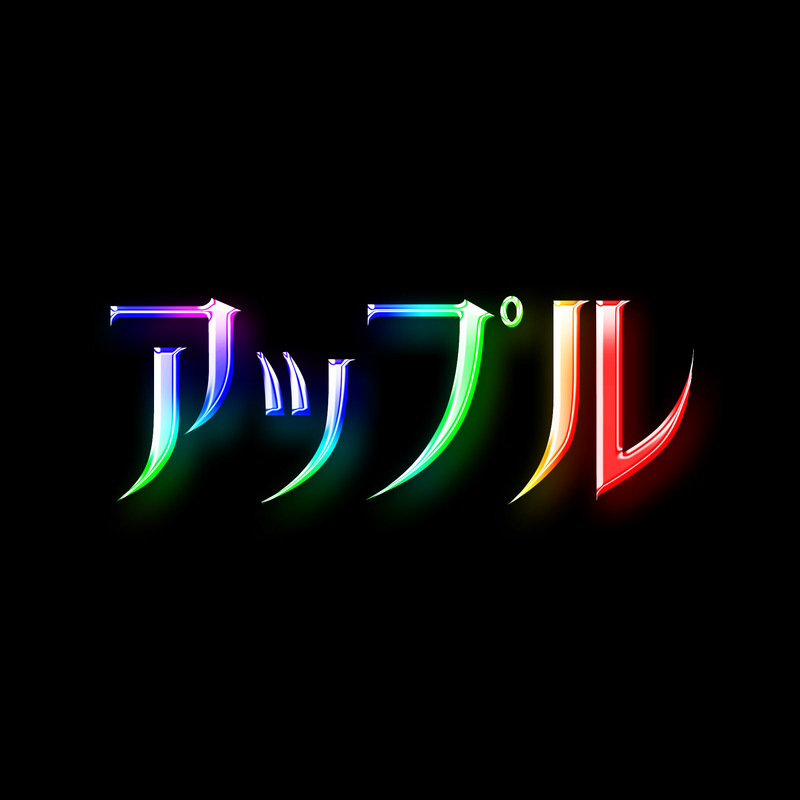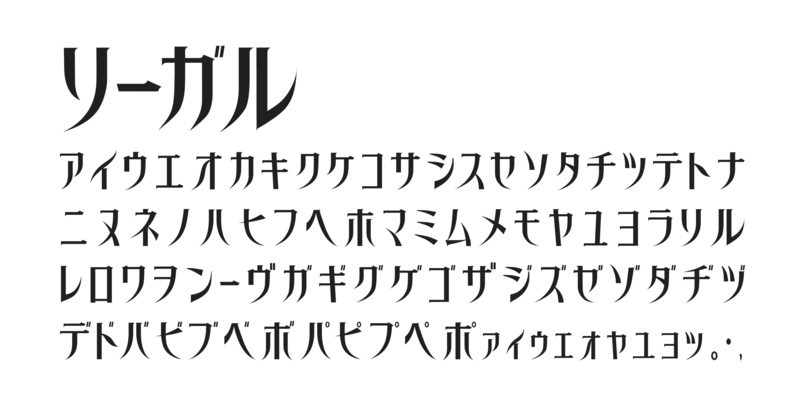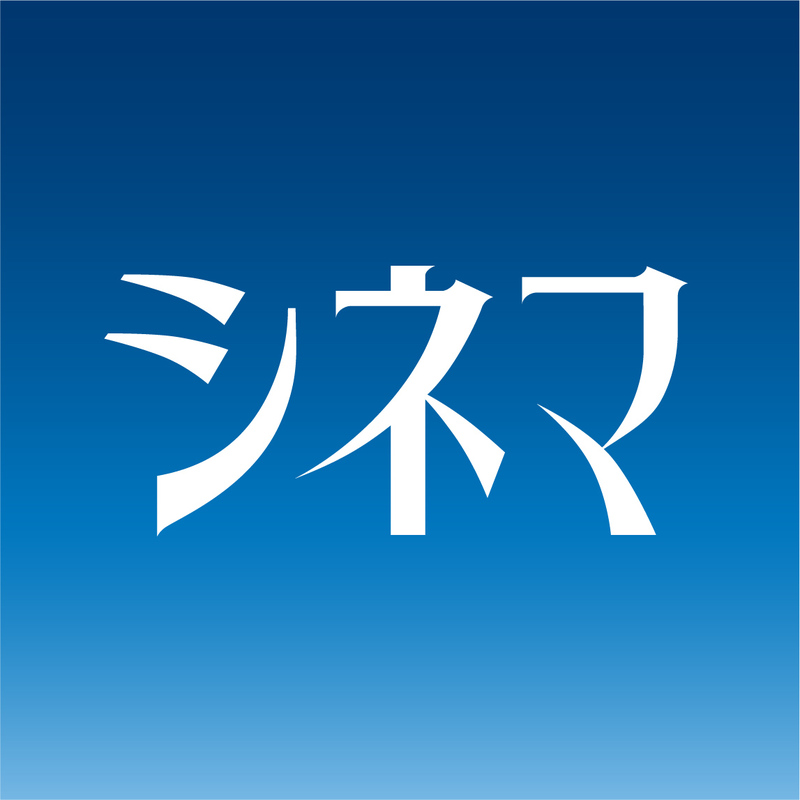
リーガル・フォント|Chiba Design|和文・欧文・デザイン書体のダウンロード販売|フォントファクトリー
商用利用可能なオリジナルフォントです。Open Type・ 2バイト・カタカナのみ。アウトライン化可能。きホラー、ミステリに関するイベントに向いています。ハロウィン・パーティやお化け屋敷のディスプレイにもどうぞ。